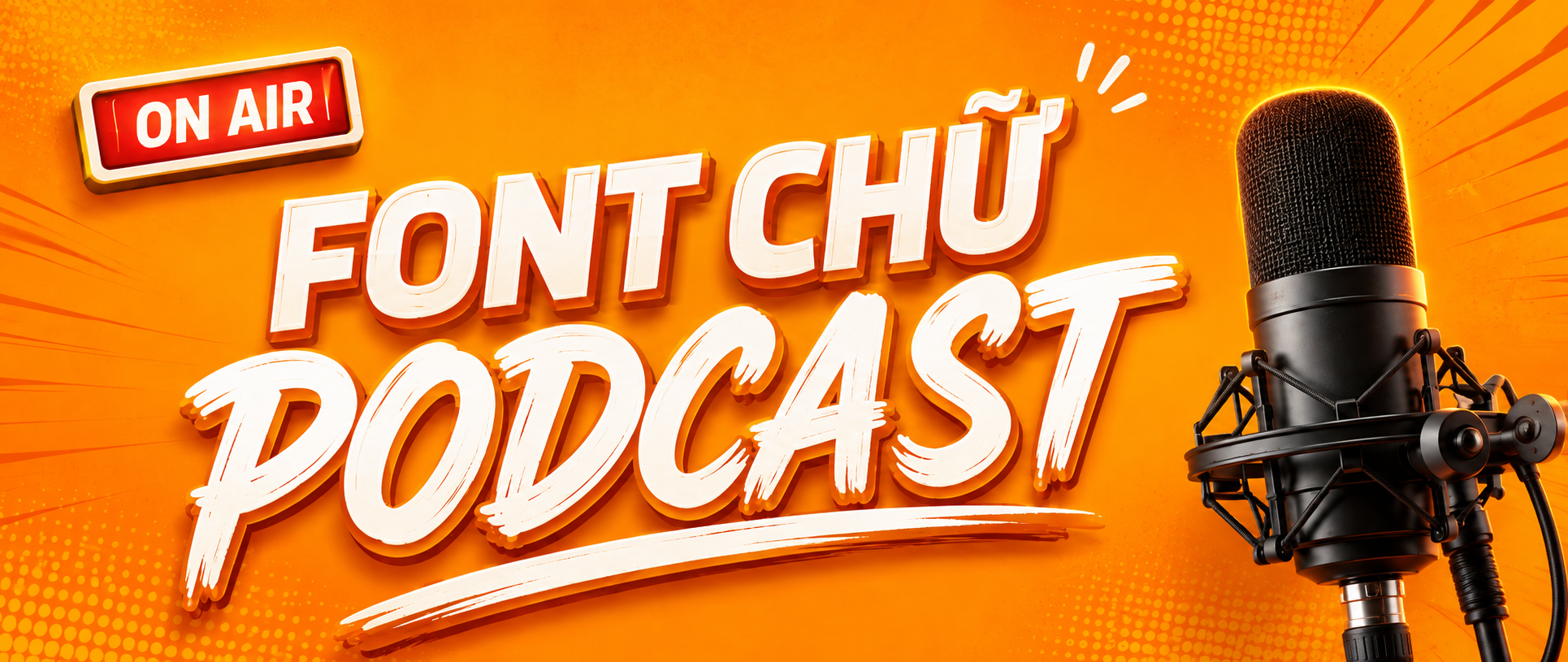
Podcast là nội dung nghe, nhưng người nghe thường quyết định bấm vào từ hình ảnh đầu tiên: cover kênh, thumbnail tập, quote card, audiogram hoặc banner social. Vì vậy, font chữ podcast cần rõ ở kích thước nhỏ, có cá tính nhận diện và hỗ trợ tiếng Việt tốt để tiêu đề tập không bị lỗi dấu.
Bài viết này gợi ý các font Việt hóa trên Font S99 cho nhiều kiểu podcast: phỏng vấn chuyên gia, kể chuyện, giáo dục, kinh doanh, công nghệ, self-help, giải trí, true crime và kênh cá nhân. Mỗi font được trình bày riêng một dòng với anchor Tải về để bạn dễ tải xuống và thử ngay trên thiết kế thật.
Trên Spotify, Apple Podcasts, YouTube, TikTok hay Facebook, người xem thường nhìn cover rất nhanh. Nếu tiêu đề tập quá nhỏ, font quá mảnh hoặc dấu tiếng Việt bị lệch, nội dung dễ bị bỏ qua dù chủ đề hay. Font podcast tốt cần vừa có nhận diện, vừa đọc được khi thu nhỏ.
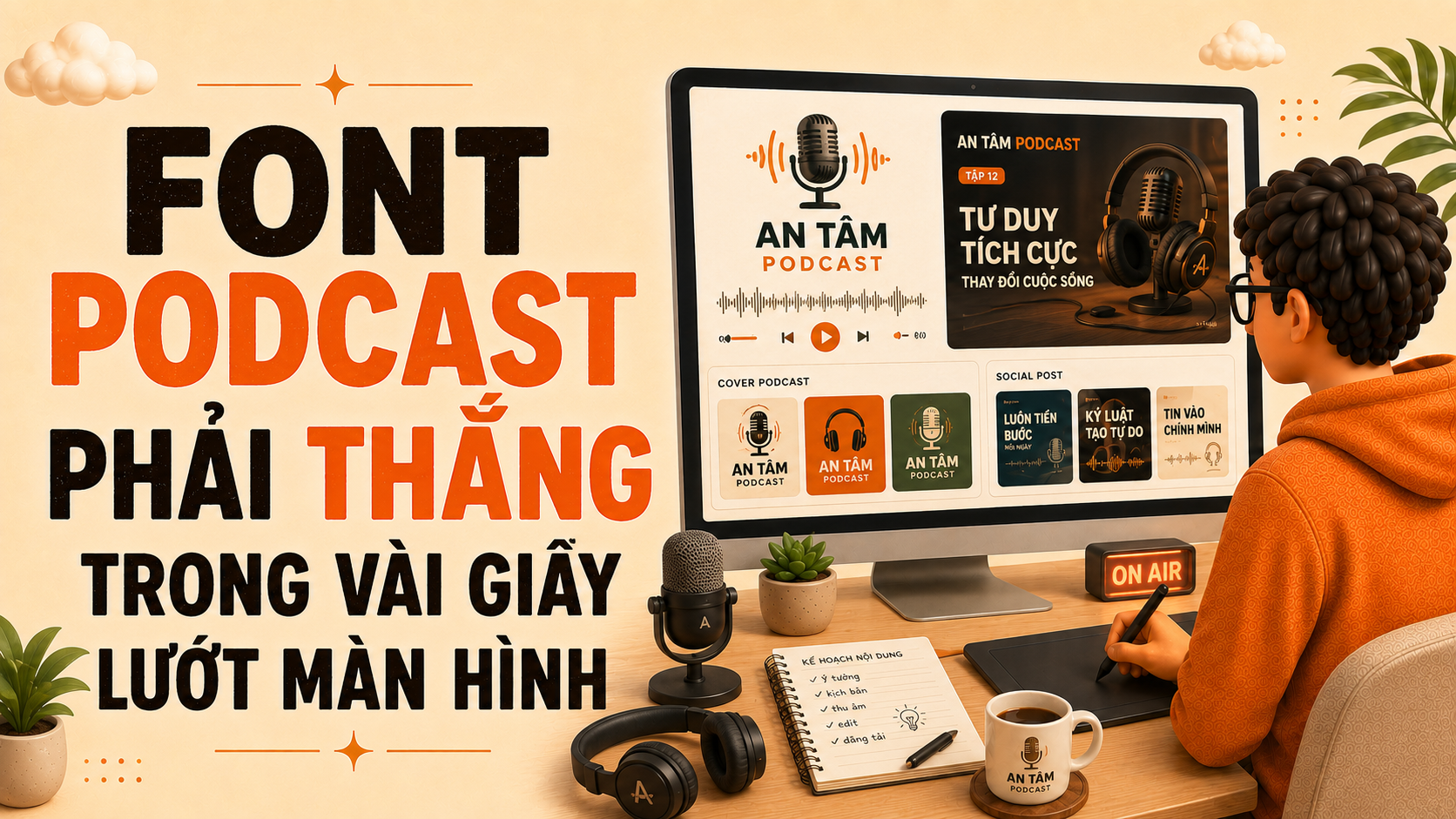
Điểm khác của podcast là phần chữ thường đi cùng ảnh chân dung, micro, sóng âm, nền studio hoặc hình minh họa. Font phải đủ mạnh để không chìm trên nền ảnh, nhưng cũng không được quá ồn làm mất cảm giác chuyên nghiệp.
Một bộ nhận diện podcast nên có ít nhất hai vai trò chữ: font headline cho tên chương trình hoặc tiêu đề tập, font phụ cho tên khách mời, số tập, ngày phát hành, trích dẫn và CTA.
Cover podcast thường hiển thị rất nhỏ trên điện thoại. Thumbnail YouTube lại cần tiêu đề to, rõ và có tương phản. Hãy thử font ở cả kích thước 1080x1080, 1280x720 và ảnh story để xem chữ còn đọc được không.
Podcast kinh doanh cần nghiêm túc và hiện đại. Podcast kể chuyện cần có chiều sâu. Podcast công nghệ cần gọn và sắc. Podcast giải trí có thể dùng font vui hơn. Chọn font theo giọng nói của kênh sẽ giúp người xem nhận ra bạn nhanh hơn.
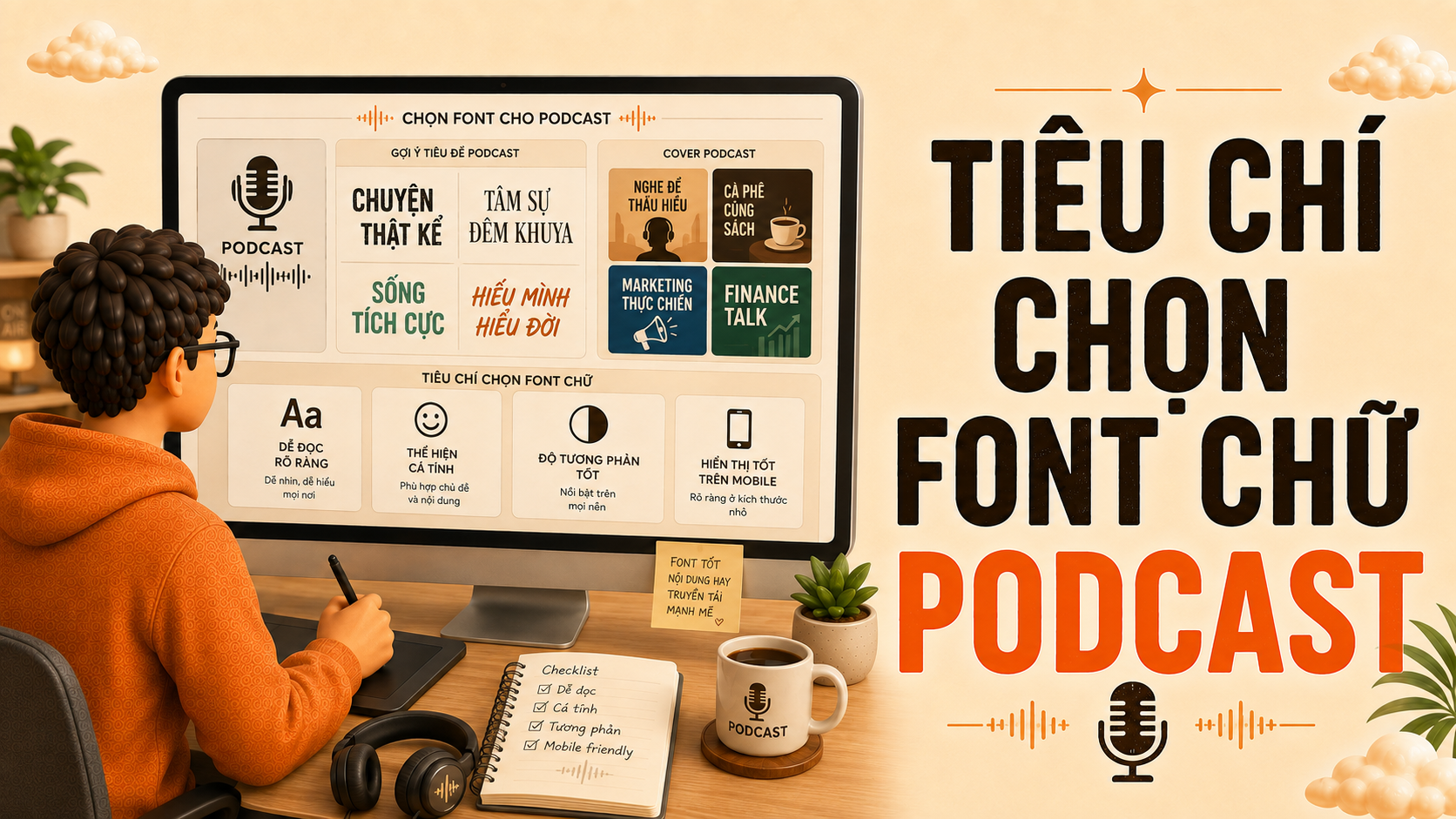
Các tiêu đề như chuyện nghề sáng tạo, tài chính cá nhân, trí tuệ nhân tạo, hành trình chữa lành, người trẻ khởi nghiệp đều có nhiều dấu. Font Việt hóa tốt giúp tiêu đề giữ được độ chuyên nghiệp khi đăng nhiều nền tảng.
Một font podcast nên dùng được cho cover, thumbnail, quote card, audiogram, slide carousel, banner sự kiện, ảnh khách mời, website và media kit. Nếu font chỉ đẹp ở chữ lớn nhưng khó đọc ở caption nhỏ, chỉ nên dùng làm font nhấn.
Nhóm font display mạnh phù hợp với tiêu đề tập cần kéo sự chú ý: chủ đề nóng, phỏng vấn nhân vật, tập đặc biệt, series mới hoặc video podcast trên YouTube. Nét chữ chắc giúp chữ không bị chìm trên ảnh chân dung và nền studio.
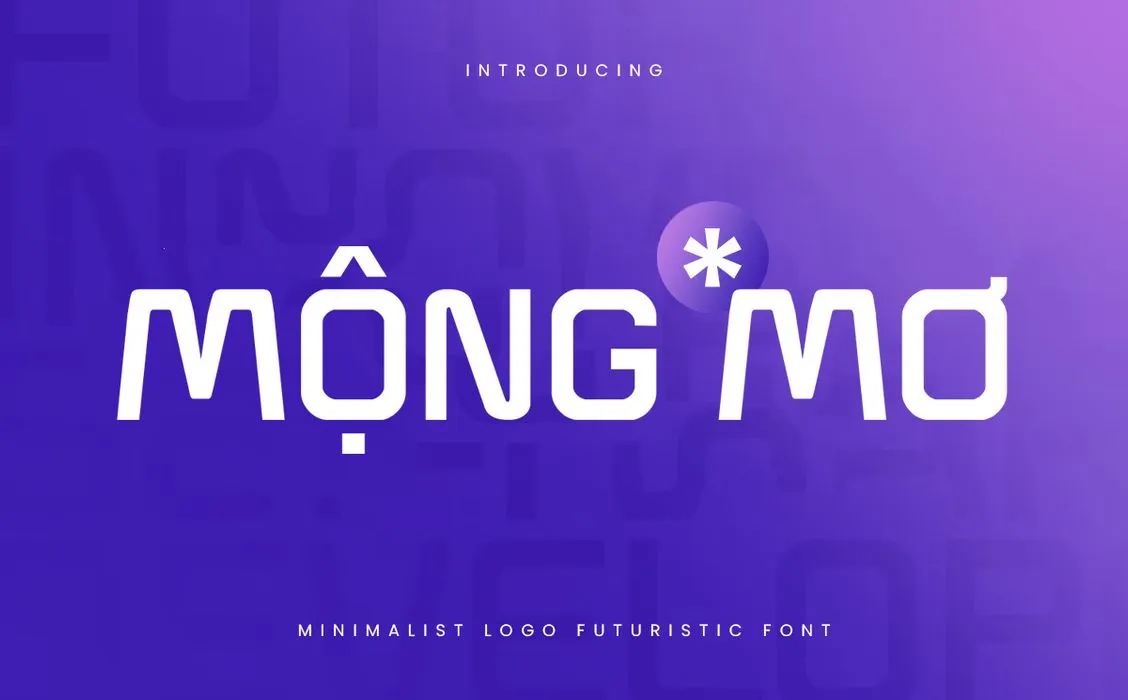
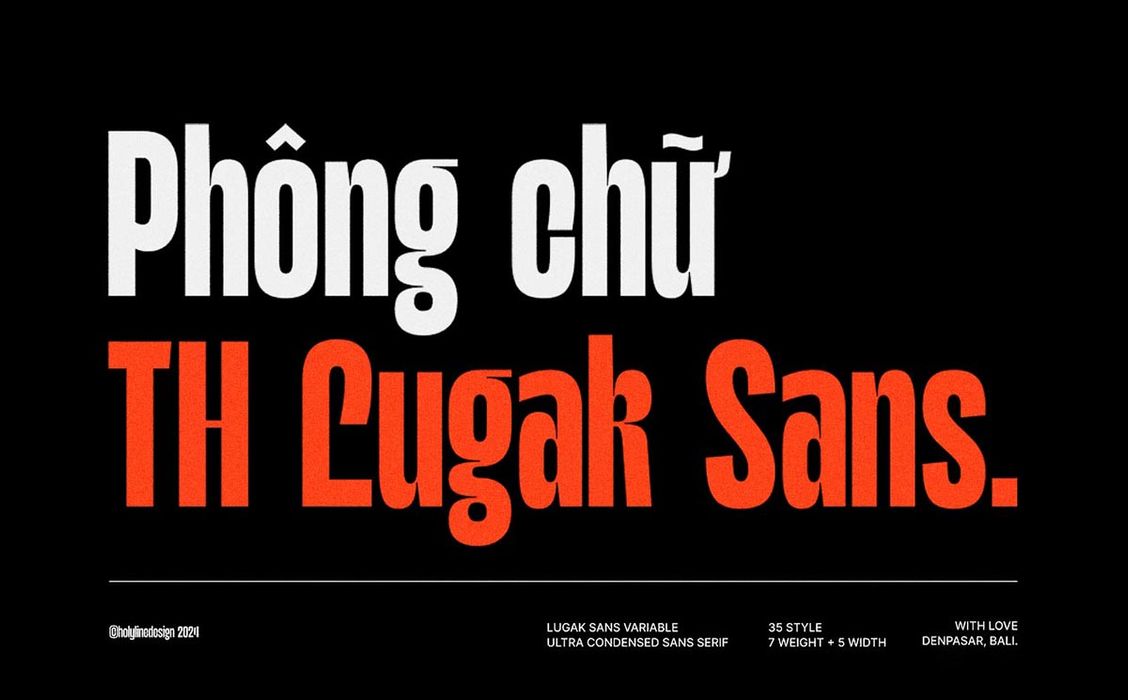
Nhóm này nên dùng cho headline ngắn như Tư duy mới, Bắt đầu lại, AI thay đổi nghề nghiệp, Sự thật phía sau, Tập đặc biệt. Với tiêu đề dài, hãy chia thành 2 dòng và dùng sans-serif rõ cho phần phụ.
Sans-serif là lựa chọn an toàn nhất cho podcast phỏng vấn, kinh doanh, giáo dục, công nghệ, marketing, tài chính cá nhân và phát triển bản thân. Nhóm này giúp hệ thống nhận diện nhìn gọn, hiện đại và dễ mở rộng qua nhiều tập.
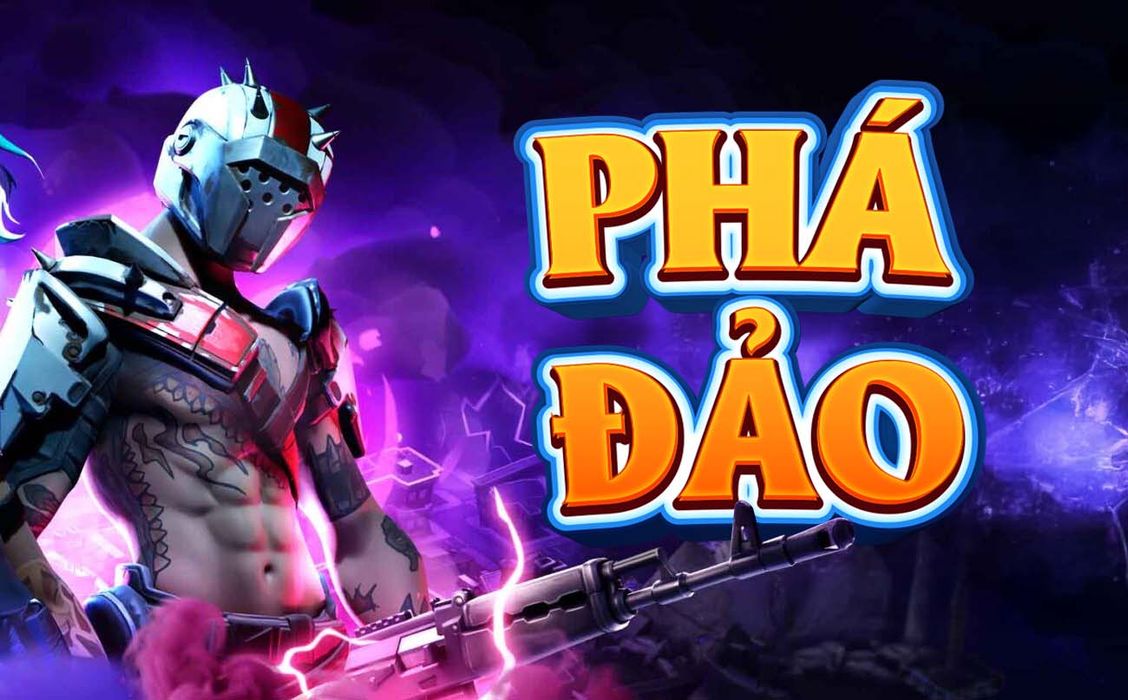
Bạn có thể dùng sans-serif cho tên kênh, số tập, tên khách mời, mô tả ngắn, CTA nghe ngay và phần chữ nhỏ trên social post. Nếu kênh đăng đều hàng tuần, sans-serif giúp template dễ tái sử dụng mà không bị mệt mắt.
Podcast kể chuyện, văn hóa, sách, lịch sử, chân dung nhân vật, tâm lý hoặc phỏng vấn chuyên sâu thường cần cảm giác có chiều sâu hơn. Serif giúp cover nhìn trưởng thành, có chất biên tập và hợp với phong cách editorial.
Font TH Selvia Genatu - Tải về
Font TH Wrigskan - Tải về
Font TH Erva Esra - Tải về
Font Playfair Display Việt hóa - Tải về
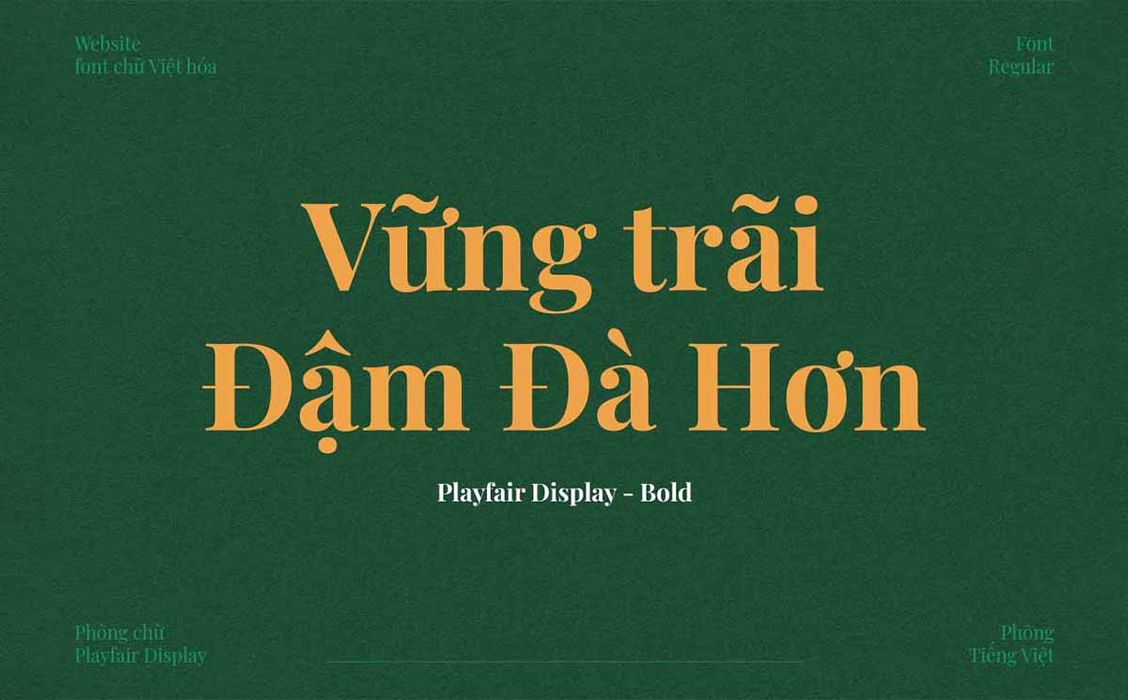
Serif nên dùng cho tên series, tiêu đề chương trình, quote card hoặc cover tập đặc biệt. Khi phối, hãy dùng serif cho headline và sans-serif cho tên khách mời, số tập, thời lượng, nền tảng phát hành để giữ độ đọc.
Công thức 1 là display mạnh plus sans-serif. Dùng font mạnh cho tiêu đề tập, dùng sans-serif cho tên khách mời, số tập và CTA. Công thức này hợp video podcast, chủ đề công nghệ, kinh doanh và nội dung cần kéo click.
Công thức 2 là serif plus sans-serif. Dùng serif cho tên chương trình hoặc quote chính, dùng sans-serif cho thông tin phụ. Công thức này hợp podcast kể chuyện, sách, văn hóa, tâm lý và phỏng vấn sâu.
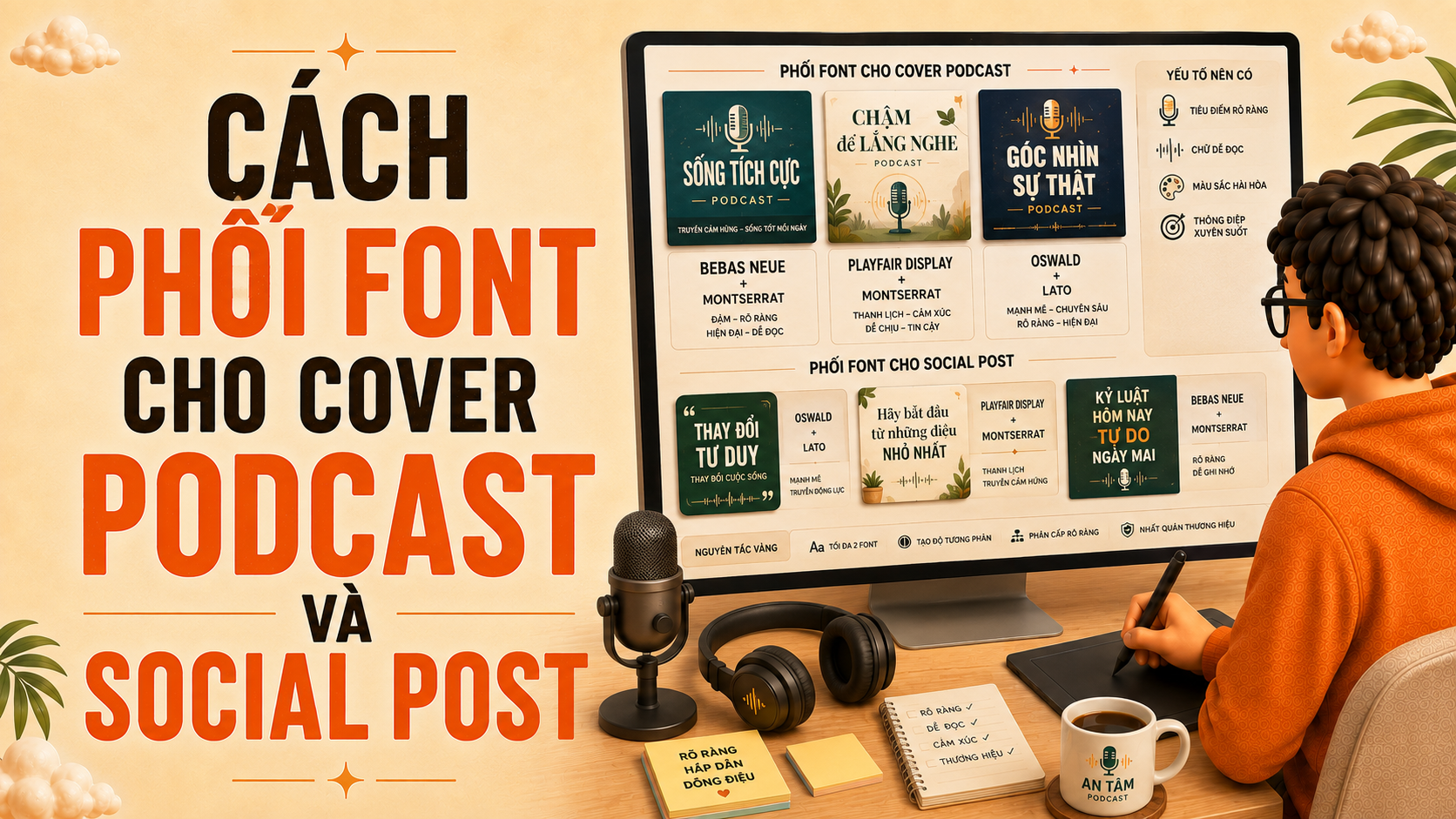
Công thức 3 là font vui plus sans-serif. Dùng font vui cho tiêu đề ngắn hoặc sticker, dùng sans-serif cho phần cần đọc rõ. Công thức này hợp talkshow đời sống, creator podcast và nội dung giải trí.
Đừng dùng quá nhiều font trên một cover. Với podcast, 2 font là đủ: một font tạo nhận diện, một font giữ độ đọc. Nếu đổi font liên tục theo từng tập, kênh sẽ khó có cảm giác series.
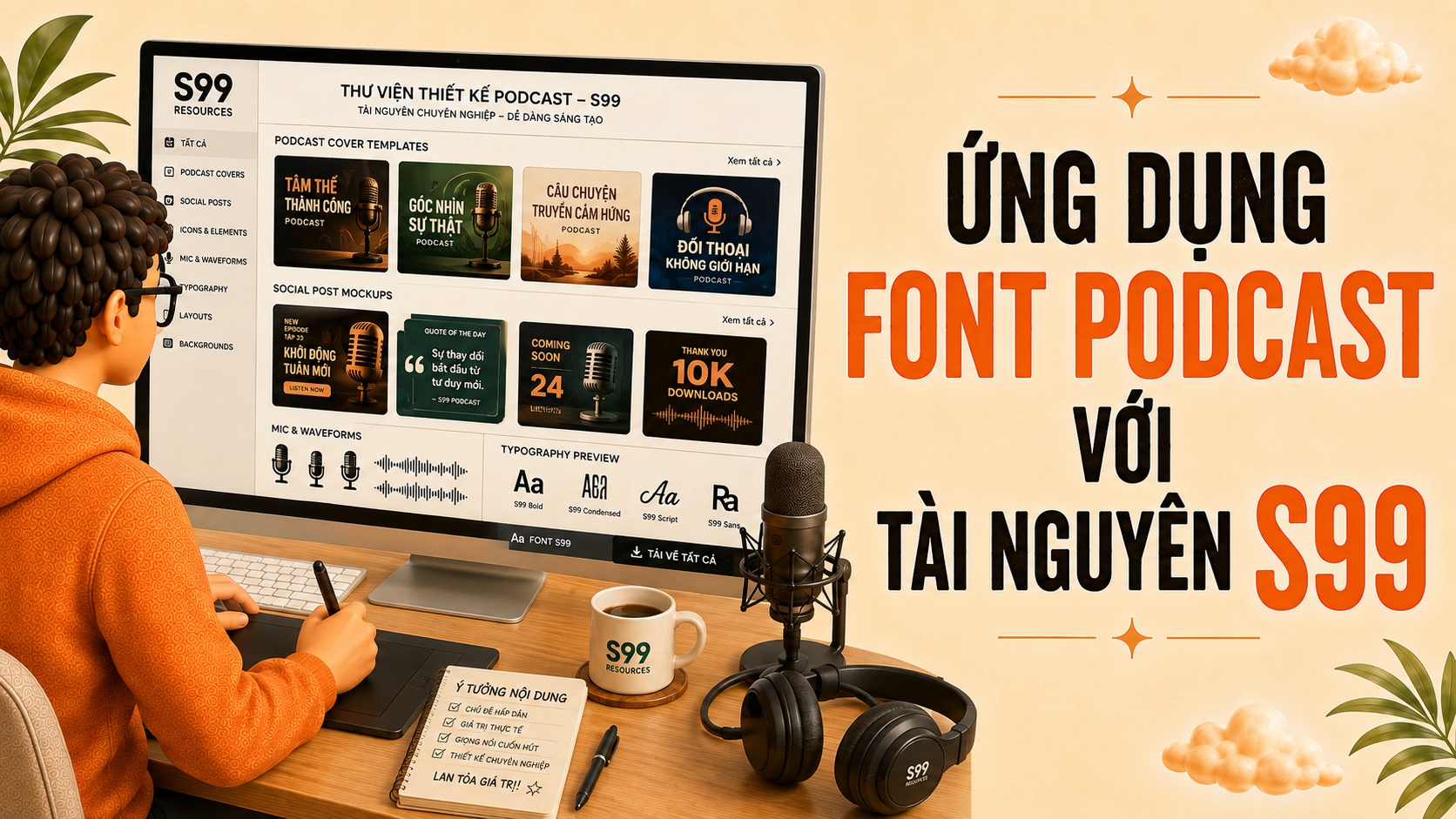
Font chữ podcast tốt phải giúp cover dễ đọc, có nhận diện và đúng giọng kênh. Hãy dùng display mạnh cho thumbnail, sans-serif cho hệ thống chuyên nghiệp, serif cho podcast chiều sâu và font vui cho nội dung giải trí.